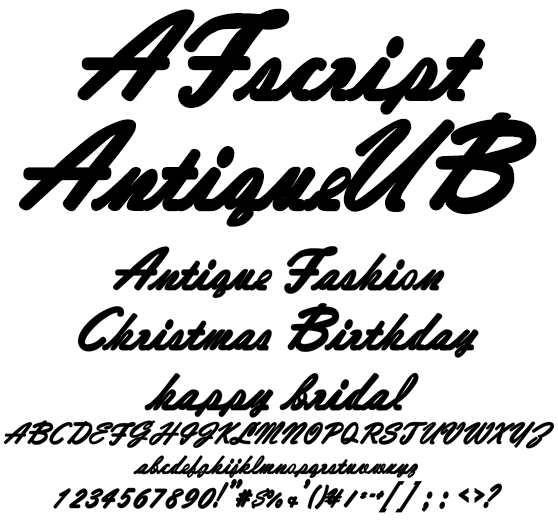
アンティークな筆記体 AFscriptAntiqueUB
AFscriptAntiqueUB
ファッション系ドキュメント、ブライダル、バースデー、クリスマスなどのイベントドキュメントに最適なお洒落なアンティーク筆記体。ウルトラボールドなエレメントが見出しでインパクトを与えます。動画テロップ、Web Serverへのアップロード、フォント共有サーバー利用、PDFエンベッド、印刷やロゴなど作成と登録、印影や彫刻、画像化後ソフトへのバンドルなど商用利用できます。